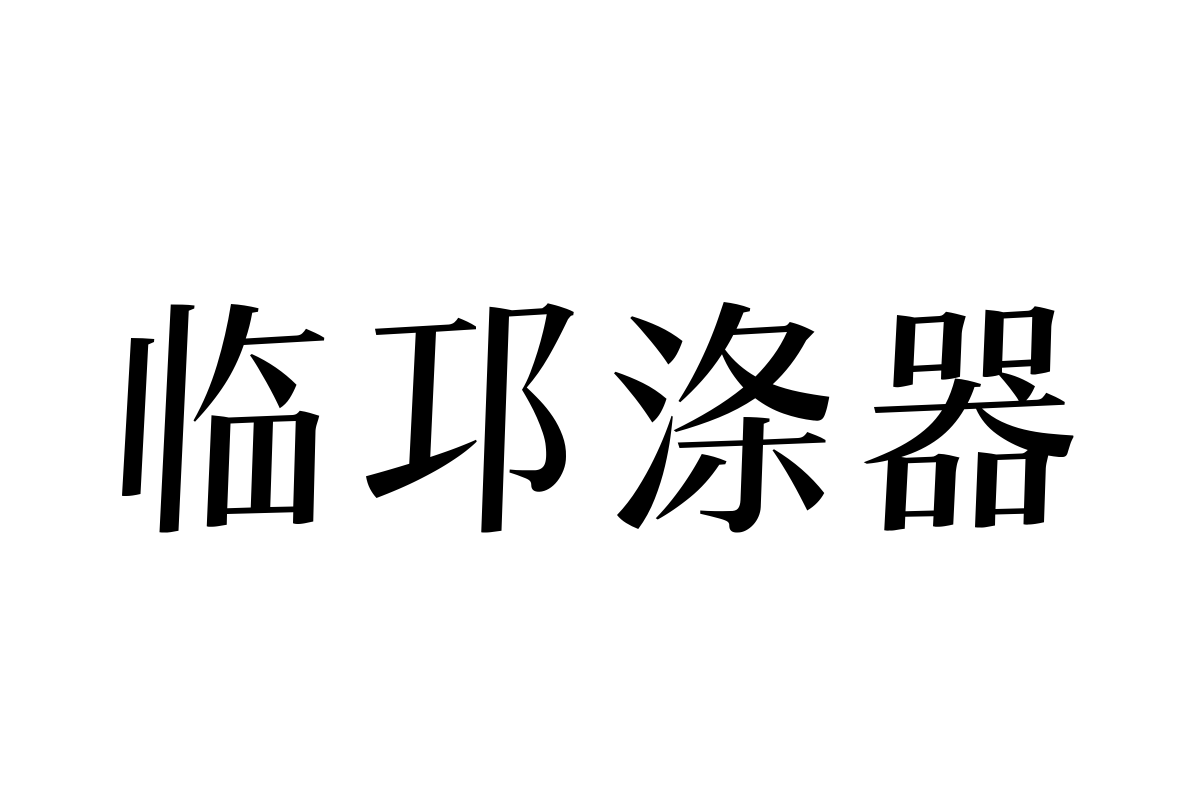
汉仪瑞意宋I_50W 是一款具有现代感的中文字体,由汉仪公司设计。这款字体的特点是字形简洁大方,线条流畅,适合用于各种商业和正式场合的印刷品。它的笔画粗细适中,既有力度又不失优雅,给人一种庄重而又不失活力的感觉。同时,这款字体也具有较高的可读性,无论是在印刷还是电子屏幕上都能保持良好的视觉效果。总的来说,汉仪瑞意宋I_50W是一款非常实用的中文字体,适用于多种场景。